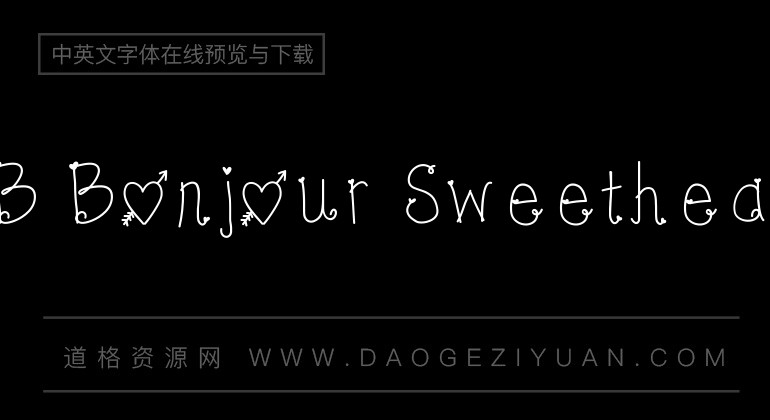
KB Bonjour Sweetheart 是一款由 Kustren 出品的欧美精致系列字体,它采用了精致的线条和色彩,具有清新可爱的外观,适用于婚礼、婚庆、婚礼邀请函、婚礼礼品等场景。它具有清新可爱的外观,能够传达出温柔、甜蜜的气氛,是一款很受欢迎的精致系列字体。内容介绍
KB Bonjour Sweetheart是一款非常不错的手写艺术字体,具有很好的视觉感,适合于文化类的宣传设计、商业类品牌的广告和产品包装设计以及个性化文字排版等较多场景。